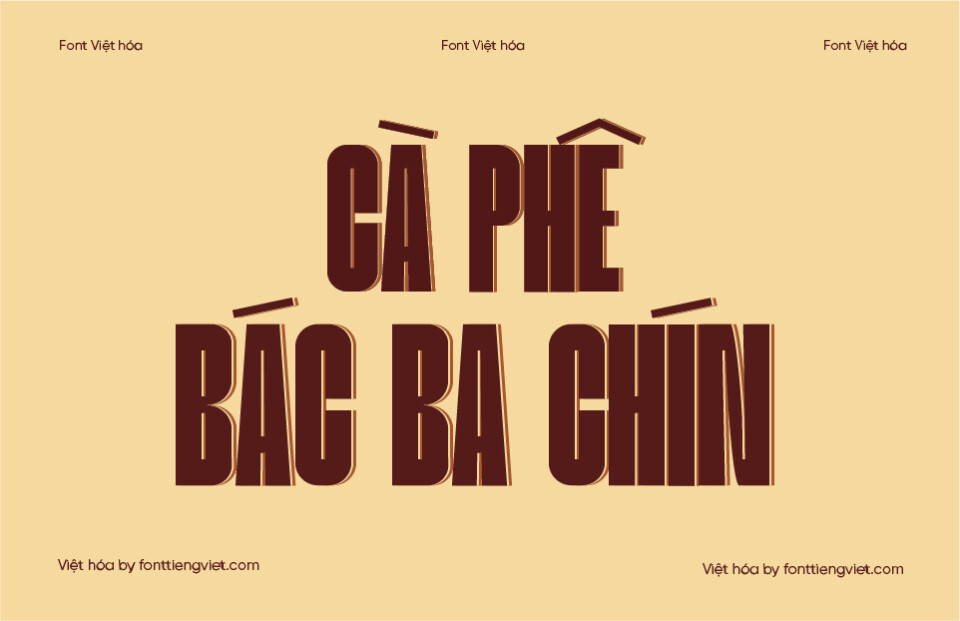
Font Việt hóa 1FTV VIP Norgate – Dấu từ font ClassiqueSaigon tạo làn gió mới cho thiết kế Việt
Giới thiệu về Font Việt hóa 1FTV VIP Norgate – Dấu từ font ClassiqueSaigon
Trong thế giới đồ họa hiện đại, việc tìm kiếm một bộ Font Chữ vừa mang nét hoài cổ vừa giữ được sự sang trọng là điều không hề dễ dàng. Font Việt hóa 1FTV VIP Norgate – Dấu từ font ClassiqueSaigon chính là giải pháp hoàn hảo cho những ai yêu thích phong cách Retro pha lẫn hơi thở đương đại. Bộ font này không chỉ nổi bật nhờ các đường nét tinh tế mà còn ghi điểm tuyệt đối nhờ hệ thống dấu tiếng Việt được trau chuốt tỉ mỉ, giúp văn bản trở nên hài hòa và chuyên nghiệp hơn bao giờ hết.
Sự kết hợp giữa Norgate và phong cách ClassiqueSaigon
Nguồn cảm hứng của bộ font này bắt nguồn từ sự giao thoa văn hóa độc đáo. Các chuyên gia đã khéo léo đưa bộ dấu đặc trưng của ClassiqueSaigon vào khung xương chắc chắn của Norgate. Điều này tạo nên một diện mạo mới mẻ, giúp người dùng dễ dàng ứng dụng vào các dự án thiết kế bìa sách, áp phích sự kiện hay các ấn phẩm quảng cáo mang đậm bản sắc Việt Nam.
Ưu điểm vượt trội của Font Việt hóa 1FTV VIP Norgate – Dấu từ font ClassiqueSaigon
Điểm mạnh nhất của bộ font này chính là khả năng hiển thị xuất sắc trên cả nền tảng in ấn và kỹ thuật số. Font Norgate vốn có cấu trúc hình học cân đối, khi được tích hợp bộ dấu chuẩn từ ClassiqueSaigon, nó loại bỏ hoàn toàn lỗi vỡ chữ hay lệch dấu thường gặp ở các font ngoại quốc. Đây là công cụ hỗ trợ đắc lực cho các bạn học sinh, sinh viên và những nhà thiết kế muốn tạo dựng dấu ấn riêng biệt trong tác phẩm của mình.